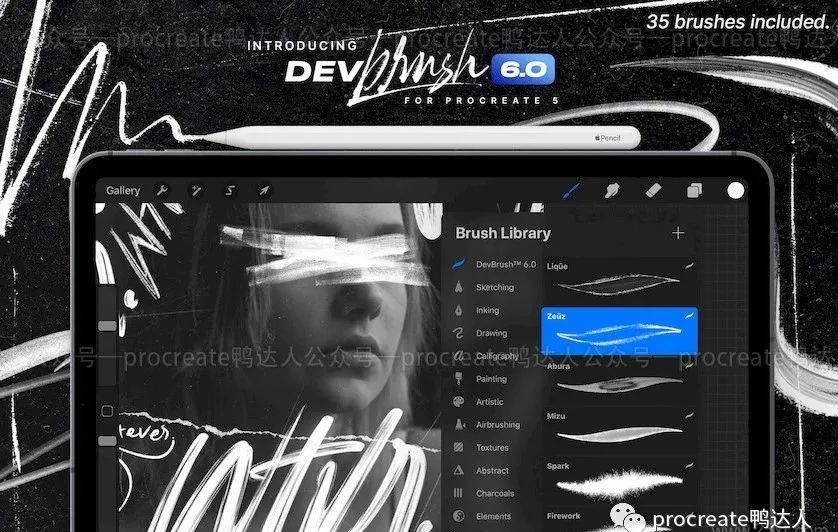
超高颜值书写笔刷送给你,别再只用系统自带字体了【316期】
一套适用于Procreate 5的DevBrush6.0手写艺术字体Procreate笔刷素材,总共有35个不同效果的书法画笔,每个画笔都有不同的书写角度,可以书写出不同的纹理效果。在iPad上借助Apple Pencil可以绘制出有专业的艺术感手写字体,创建许多不同的样式-图形字体,经典墨水,富有表现力的纹理设计等等!